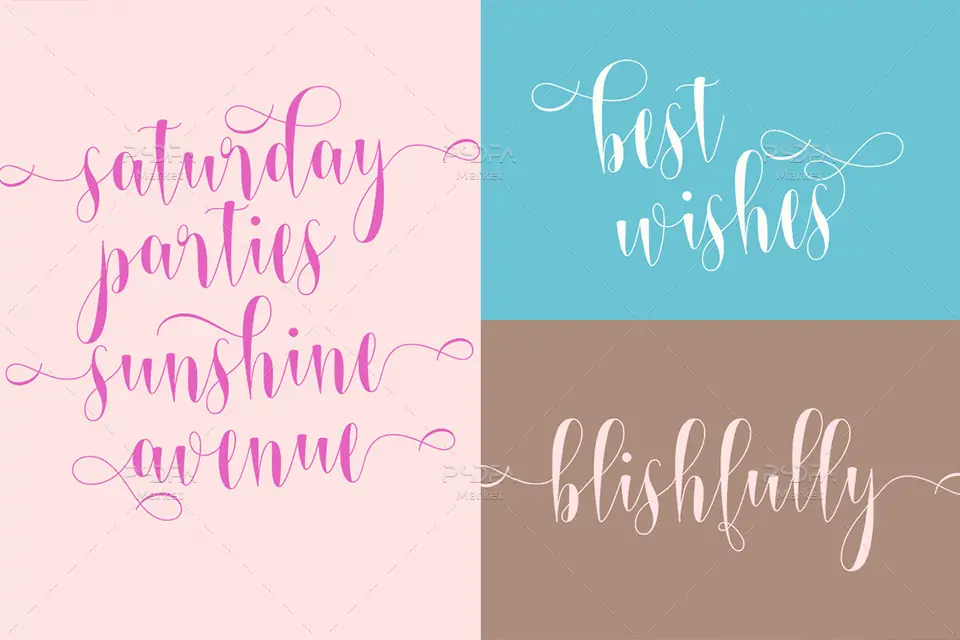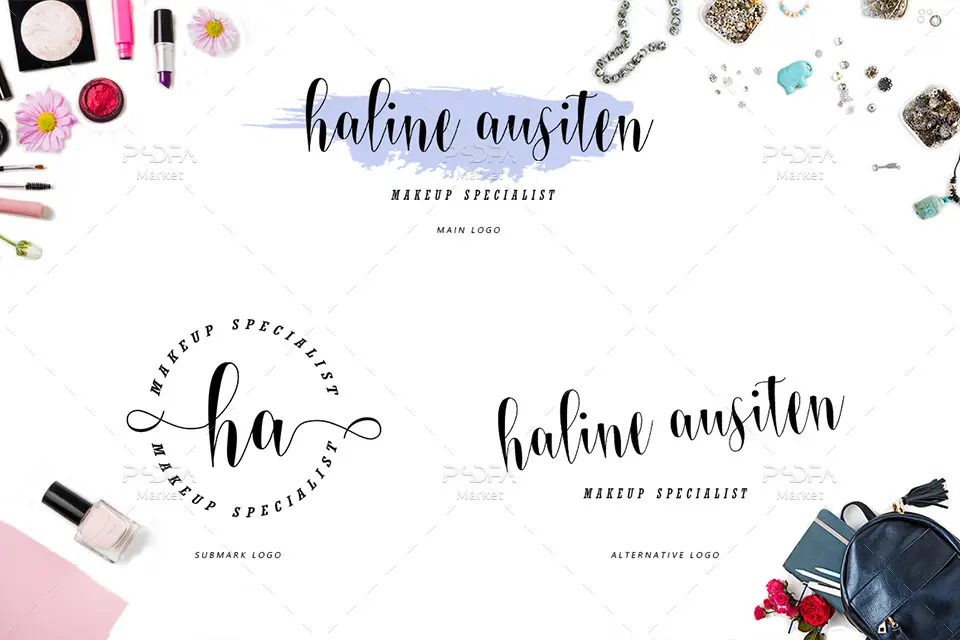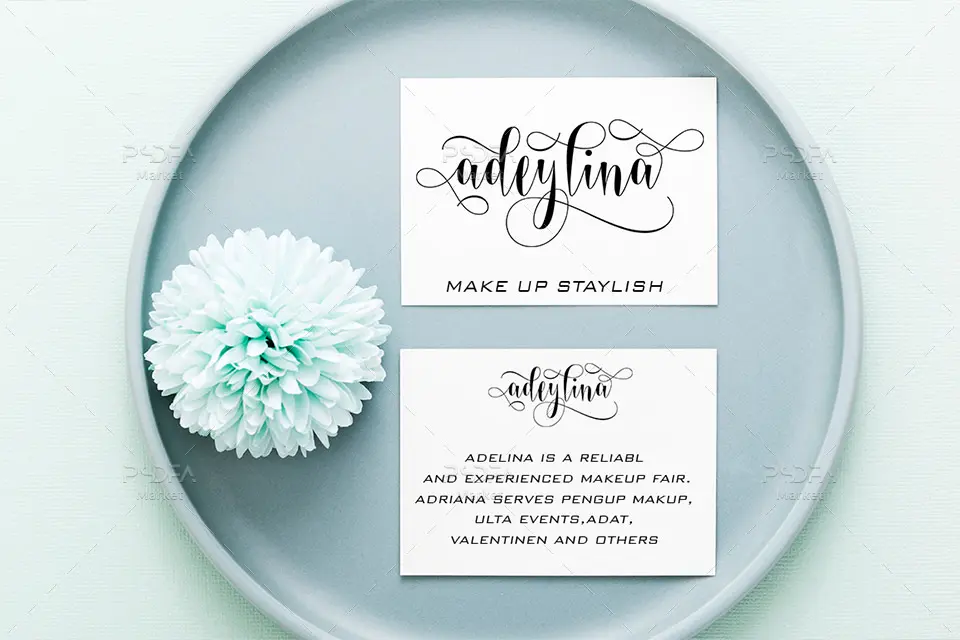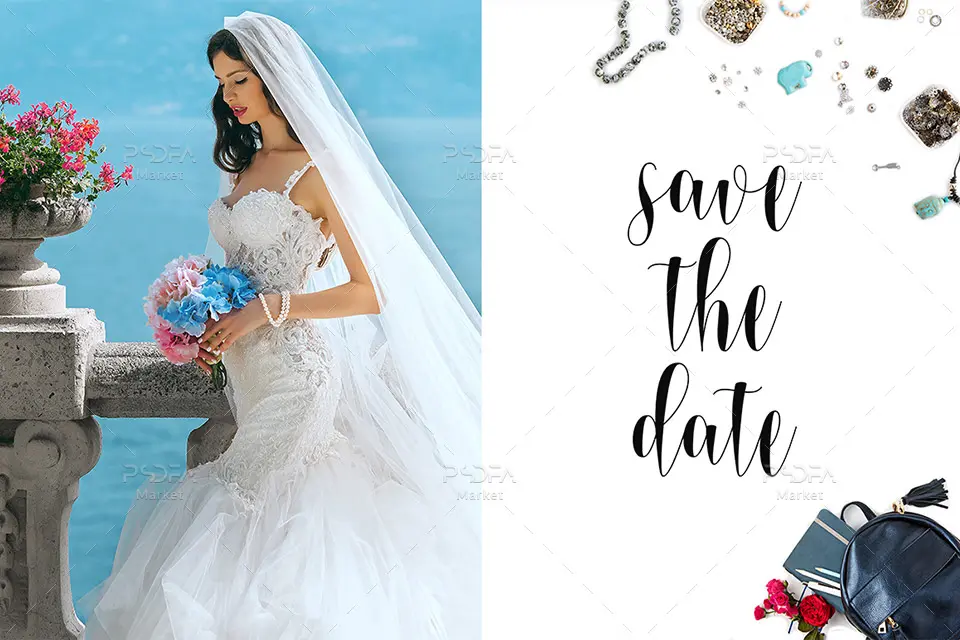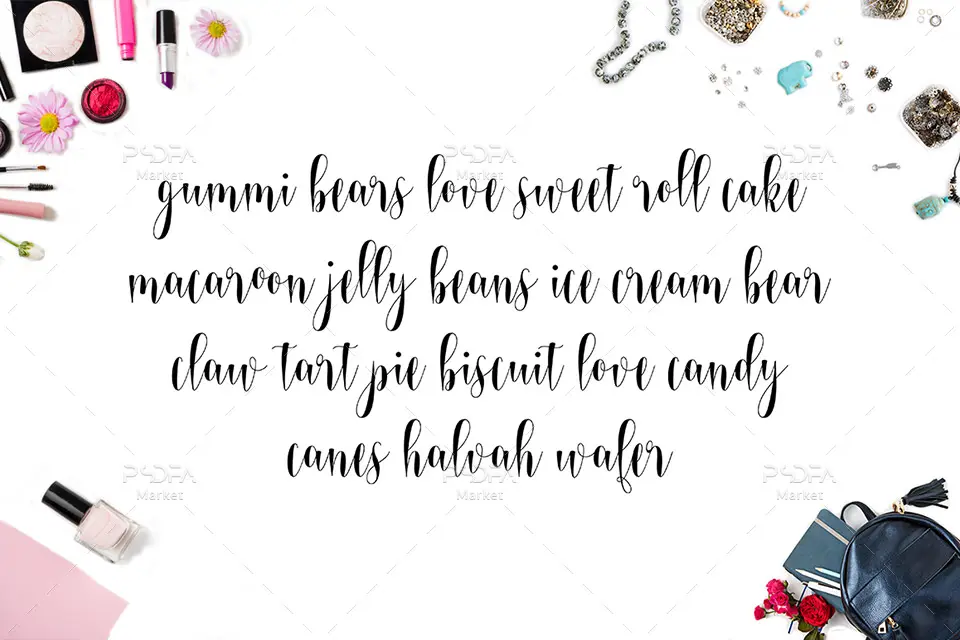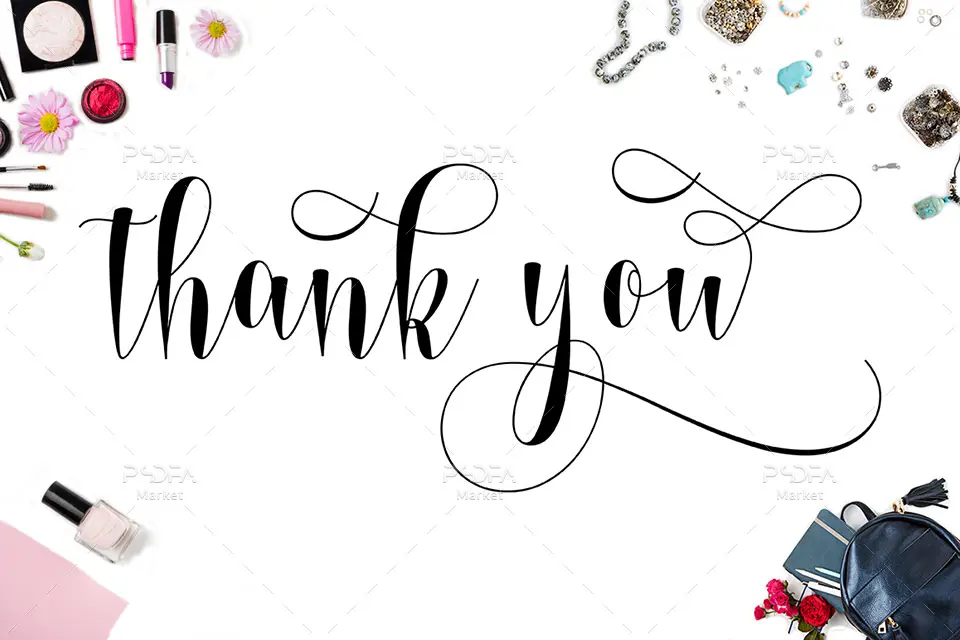
اسکریپت فونت دستنویس Adeylina یک قلم زیبای انگلیسی است که میتوانید از آن در طرح و پروژههای گرافیکی خود استفاده کنید. این فونت زیبا با 2 فرمت otf, ttf بر روی سایت قرار گرفته است که پس از نصب یکی از این دو فایل در پوشه فونتهای سیستم قادر به استفاده از آن در تمام نرمافزارهای گرافیکی و ویرایشگر متن همچون فتوشاپ، ایلوستریتور، افترافکت، پریمیر، مجموعه نرمافزار آفیس و … خواهید بود. فونت Adeylina در وزن معمولی یا Regular طراحی و ساخته شده است که میتوانید از آن در طراحی کارت عروسی، کارت تبریک، کارت ویزیت، تراکت، بنر، بروشور، انواع پوستر، تقویمهای رومیزی و دیواری، طراحی لوگو، طراحی سایت و … استفاده کنید.